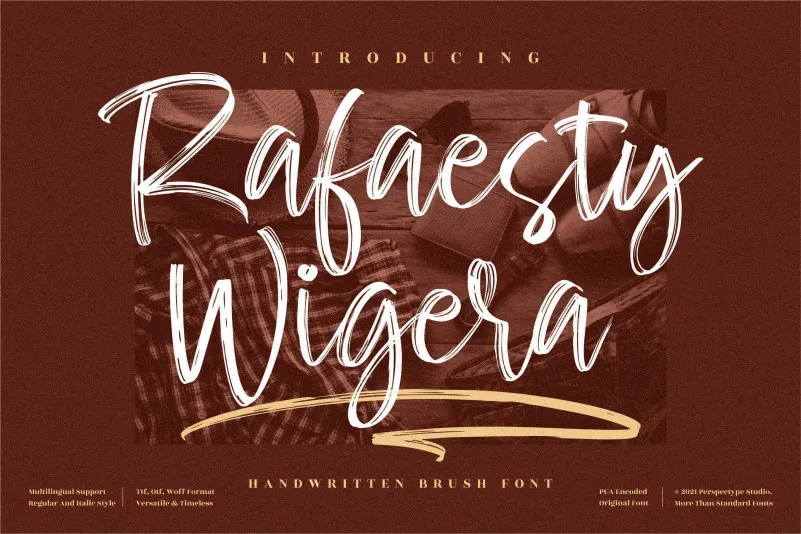
Rafaesty Wigera Font – Download Grátis
Aqui está uma versão em português do Brasil, envolvente e natural para a página de download da font ‘Rafaesty Wigera Font’, categoria Brush Fonts: Esta Rafaesty Wigera é uma bela tipografia feita à mão com um toque delicado. Ela oferece caracteres relaxados e asimétricos, idealizando a personalização em qualquer projeto gráfico que precise daquela sensação única e especial. Para criadores de design amantes dos detalhes, esta font será certamente uma opção de escolha, capaz de dar um toque inconfundível à sua obra. Seja para criar cartazes, infográficos ou apenas textos em seu website pessoal, a Rafaesty Wigera é perfeita para aqueles que buscam uma personalização única e autêntica na sua arte digital.